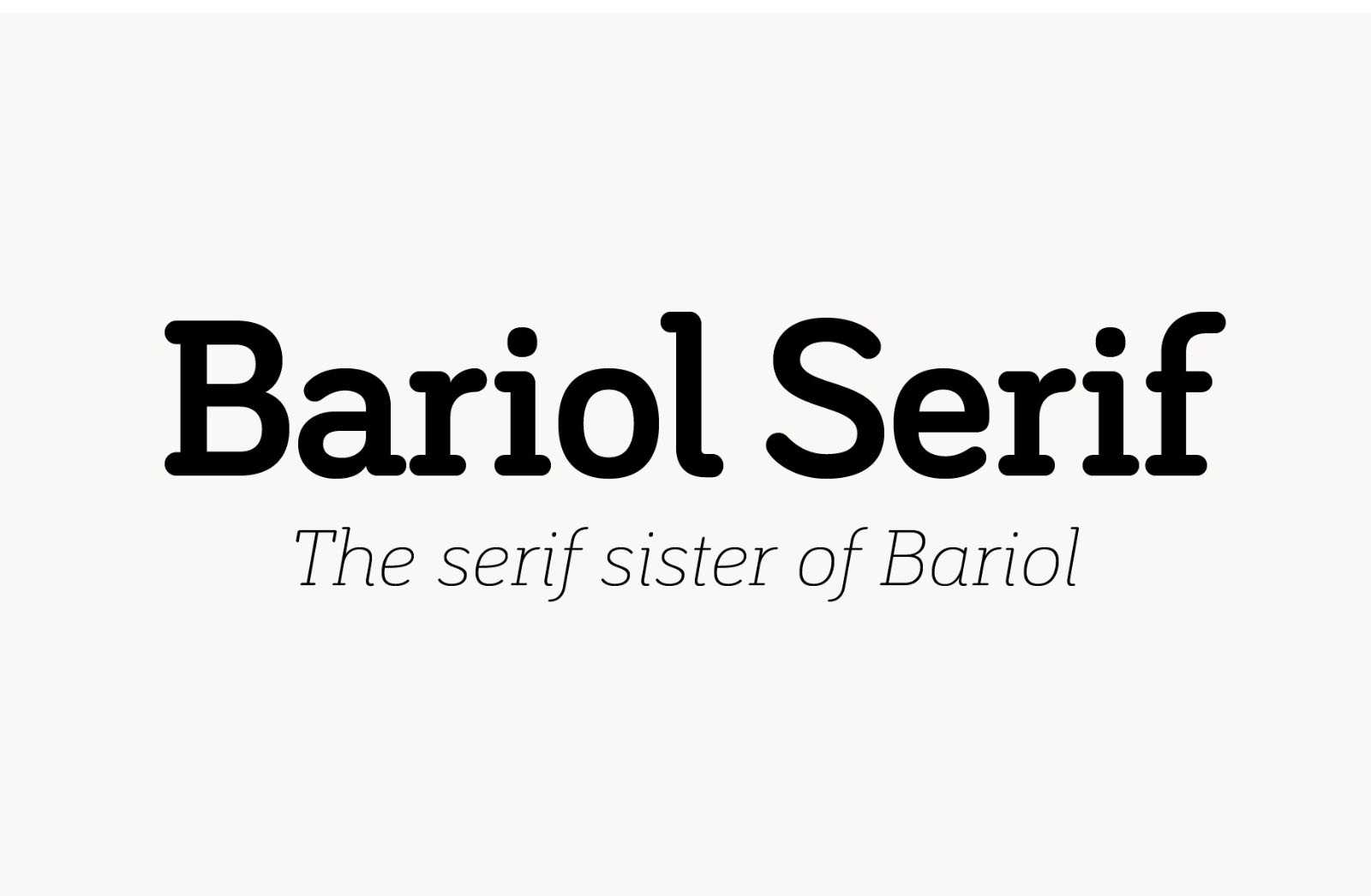
Bariol Serif Modern Typeface – Download Grátis
Bariol Serif é uma nova irmã serif do famoso Bariol font. Esta fonte bem planejada preserva o estilo do seu irmão sans serif e oferece quatro pesos e itálico. É uma família de fontes serif moderna e funcional, perfeita tanto para aplicações desktop quanto para web. Oferece uma boa leitura, independentemente do dispositivo. Além disso, inclui recursos de tipografia numérica, como frações predefinidas, notáveis, superscritos e inferiores científicos. E também oferece suporte a muitas línguas. Bariol Serif é uma escolha perfeita para designers que buscam uma fonte moderna e legível, sem abrir mão dos benefícios do estilo serif. Descubra como este recurso gráfico transformará sua próxima página ou aplicativo.